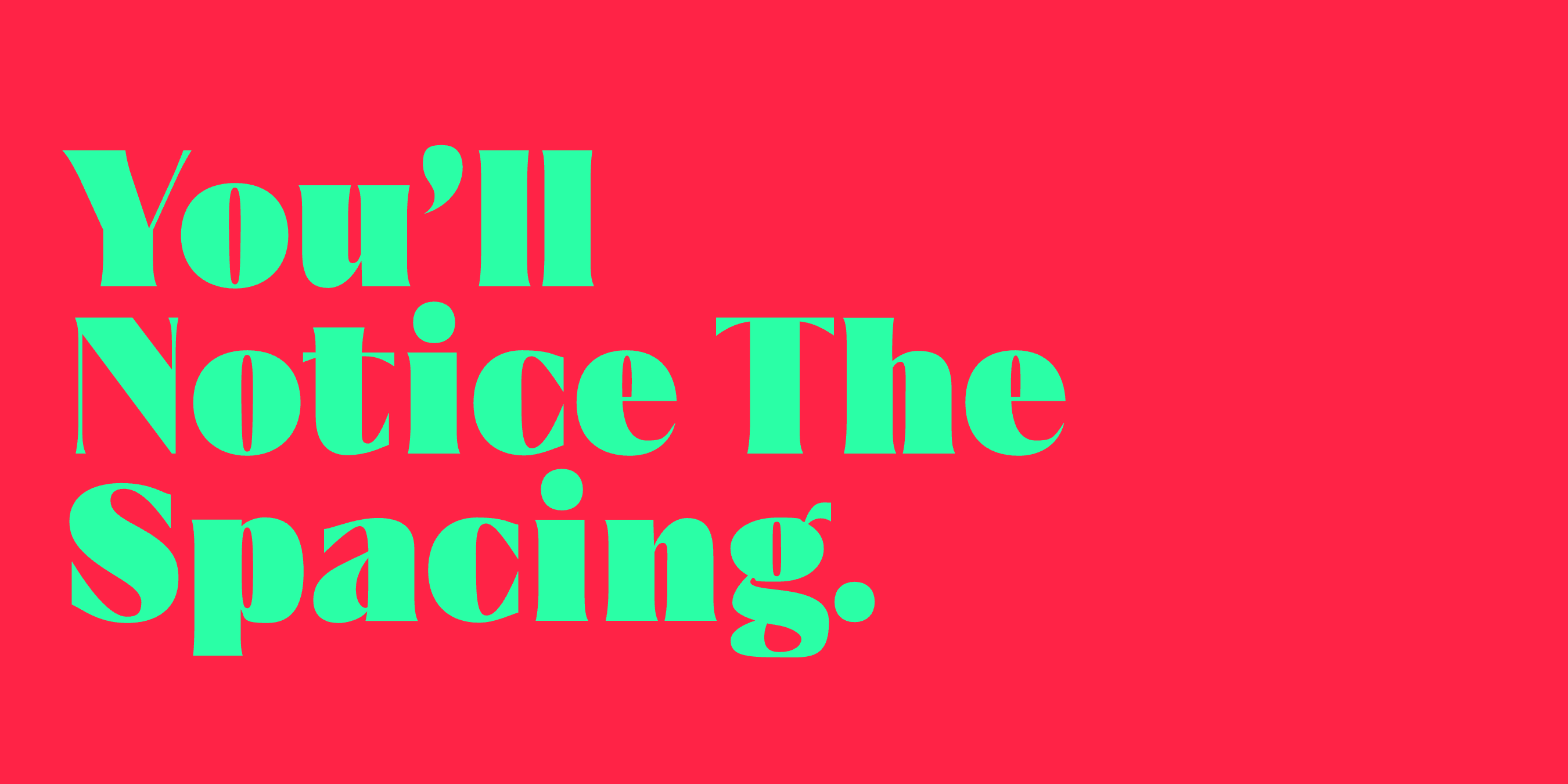
Designer achten auf Kleinigkeiten. Die Neigung eines kleinen ‚a‘, ob die Abstände Luft lassen, wie ein ‚g‘ in seine Schleife hinabläuft. Was den meisten bei der Schriftwahl für ein Projekt in Ordnung erscheint, kann sich für Designer deshalb trotzdem falsch anfühlen.
Diese Liste ist mit genau diesem Blick entstanden. Jede Schrift hier stammt aus unserem eigenen Katalog und wird von Designern, die wir kennen, für Branding, Editorial und Verpackungen genutzt. Sie greifen nicht nur wegen des Aussehens zu diesen Schriften, sondern wegen der handwerklichen Arbeit dahinter: Alternativen, die echte Probleme lösen, Schnitte, die gut zusammenpassen, und Formen, die in jeder Größe funktionieren.
Bauhaus Soft
Eine kräftige, organische Serifenschrift mit gerade genug Kontrast, um hochwertig zu wirken, ohne ihre Wärme zu verlieren. Sie passt dort, wo das Gewicht einer Serifenschrift und eine weichere Seite zugleich gefragt sind. Lässt sich gut mit Sans-Serif-Schriften in Markensystemen und Editorial-Layouts kombinieren.
Eine scharfe, schmale Serifenschrift für redaktionelle Titel. Die Proportionen bleiben in großen Display-Größen markant und auch in kleinerem Text lesbar. Eine gute Wahl für einen Mode- oder Beauty-Look, der nicht beliebig wirkt.
Eine scharfe, schmale Serifenschrift mit langen Endstrichen. Die engen Proportionen geben Aezra viel Persönlichkeit, besonders in großen Größen. Die Endstriche leisten den Großteil der Arbeit und geben der Schrift eine redaktionelle, fast architektonische Haltung.
Eine runde Schrift mit starkem Kontrast, die zwischen eleganter Display-Schrift und freundlicher Nahbarkeit liegt. Der Kontrast zwischen dicken und dünnen Strichen gibt ihr Präsenz, die abgerundeten Ecken halten sie warm. Geeignet für Beauty-Marken und Verpackungen.
Eine humanistische Sans mit Kontrast: Sie hat die geometrische Klarheit einer Sans-Serif, aber Striche, deren Stärke wie bei einer Serifenschrift variiert. Sie passt dort, wo die Lesbarkeit einer Sans-Serif mit etwas mehr handwerklichem Charakter gefragt ist.
Eine moderne Serifenschrift mit eleganten Proportionen. Die Striche wirken selbstbewusst, aber nicht dramatisch. Für Editorial-, Mode- und Beauty-Projekte, die zurückhaltend raffiniert wirken sollen statt laut.
Eine luftige, moderne Sans-Serif mit weichen Innenecken. Die Weichheit gibt ihr in Textgrößen Wärme, die geometrische Grundlage hält sie in Display-Größen klar. Eine gute Wahl für Tech-Marken, die menschlich wirken möchten.
Eine geometrische Sans-Serif mit fließenden Punzen (den Innenräumen von Buchstaben wie ‚o‘ und ‚e‘). Die Punzen fließen auf eine Weise, wie es bei den meisten geometrischen Sans-Schriften nicht der Fall ist, und das Ergebnis wirkt zugleich freundlich und modern.
Eine kräftige, spitze Sans-Serif mit scharfen Alternativen. Die dreieckigen Spitzen geben ihr Kante, und mit den Alternativen lassen sich für Überschriften noch schärfere Buchstabenformen einsetzen. Passt gut zu Tech, Sport und selbstbewussten Marken.
Eine architektonische Sans mit geschnittenen Diagonalen: Die diagonalen Striche enden gerade abgeschnitten statt gerundet. Das Detail ist dezent, gibt Ark aber einen strukturierten, fast konstruierten Charakter. Geeignet für designorientierte Marken.
Neben dem Aussehen gibt es bei der Wahl einer Schrift für ernsthafte Arbeit ein paar Punkte zu prüfen. Hat sie die nötigen Schnitte? Gibt es alternative Buchstabenformen für schwierige Kombinationen? Funktioniert sie in Textgrößen, nicht nur in Überschriften? Ist das Dateiformat aktuell?